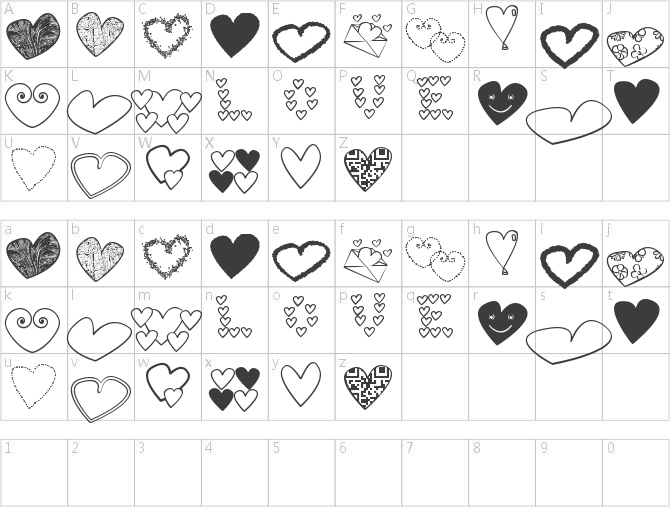
hearts-shapess-tfb 詳情頁(yè)
hearts-shapess-tfb字體字庫(kù)是一款讓人賞心悅目、百看不厭的英文字體,適合各類廣告和產(chǎn)品包裝設(shè)計(jì)應(yīng)用,字體大小0.17MB,格式為ttf字體,上傳用戶是KISEKI,作者/版權(quán)方為未知